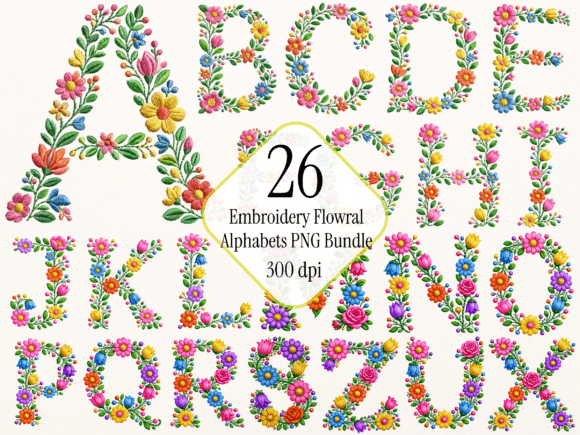
Floral Embroidery Alphabet PNG Bundle
Encontrar los elementos de diseño adecuados puede ser un desafío, pero Floral Embroidery Alphabet PNG Bundle ofrece una colección excepcional que eleva tu trabajo al instante.
Elaborado con precisión, Floral Embroidery Alphabet PNG Bundle proporciona vectores limpios, tipografía suave y una licencia comercial para tu tranquilidad.